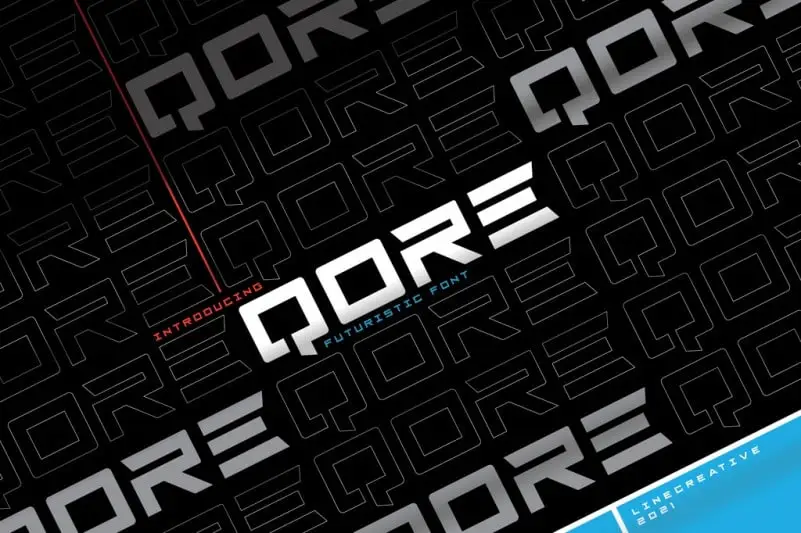
A Qore Display Font é uma tipografia sans-serif inspirada nas famosas logomarcas de tecnologia e marcas que possuem características muito fortes. Inspirado na estética poderosa desses símbolos, essa fonte apresenta um estilo sóbrio e alegre ao mesmo tempo, adequada para qualquer projeto visual que deseje expressar sua identidade de marca com vigor e originalidade. Com todas as letras maiúsculas, ela oferece alternativas estilísticas que garantem uma ampla gama de usos. A Qore Display Font é perfeita para criação de logomarcas, design de roupas ou até mesmo rótulos de produtos que buscam destacar-se no mercado. Com suporte a múltiplas línguas, ela se encaixa em qualquer projeto global que deseje incorporar elementos de marca distintos e eficazes. Seja para uma camiseta personalizada ou um site respeitável, essa fonte é perfeita para quem busca criar uma presença visual imediata e memorável.